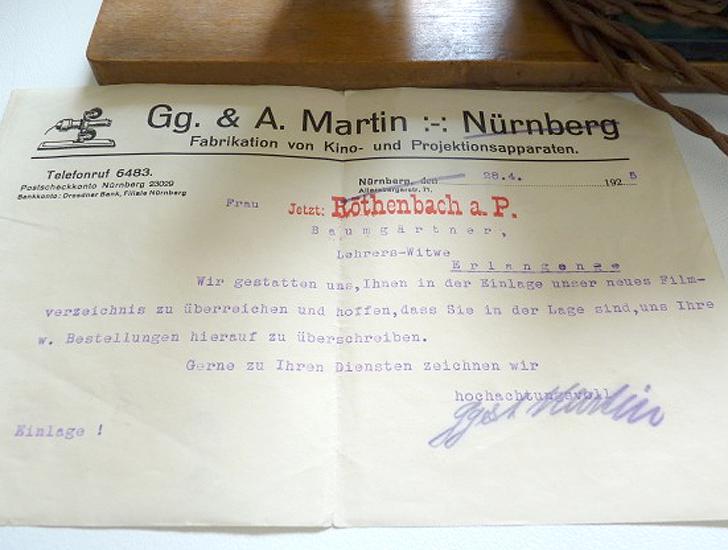
auf der Seite des Kameramuseums bin ich auf folgendes Anschreiben der Firma Gg. & A. Martin gestoßen:
Hat diese Doppelpunkt-Strich-Kombination eine bestimmte Bedeutung?
Als sinntragendes Zeichen ist mir :-: nicht bekannt. Aber warum sollte das eine dumme Idee sein?  Ziermaterial aus dem Setzkasten herzustellen, ist durchaus sinnvoll. Und wenn es eine dumme Idee wäre, warum sollte es die des Setzers sein? Mir werden übrigens nicht ganz selten Einfälle angetragen, für die sich dann jemand anders findet, der sie in eine Drucksache verwandelt, weil ich sie nicht für gut genug dafür halte. Schlecht an diesem Briefbogen hier ist nur der rücksichtslose Halbgeviertsatz.
Was macht jemand, der von Beruf Lehrerswitwe ist? Filmvorführungen? Frau Baumgärtner kann man sicherlich nicht mehr fragen, außer sie war 1925 eine überaus junge Witwe und wurde wirklich alt.
Wie im (jetzt funktionierenden) Link zu sehen ist, stellte die Firma auch Diaserien her, die für den Unterricht geeignet sind. Vielleicht wurde die Adresse weiter im Katalogverteiler geführt.
Mein Großvater war Schuhmacher und starb Anfang der 50er-Jahre; meine Großmutter bekam noch bis in die 80er-Jahre (als „Schuhmacherswitwe“) Prospektmaterial über Lederpflegemittel, Schnürsenkel und anderes...